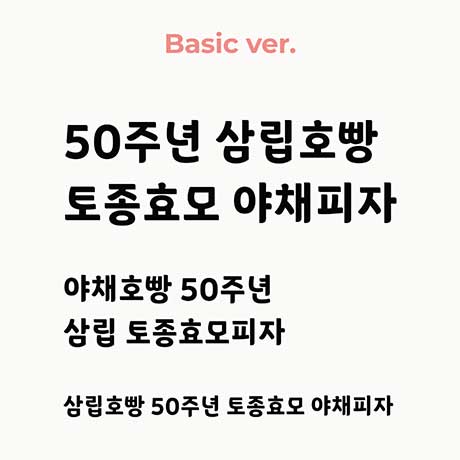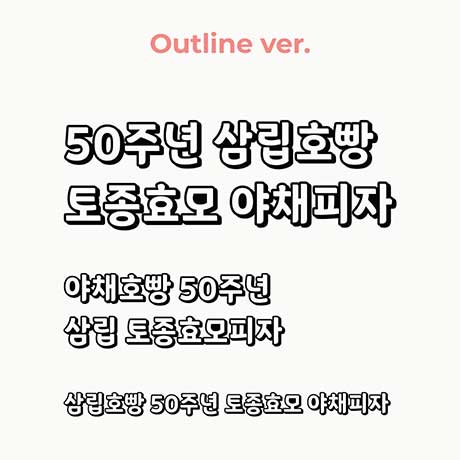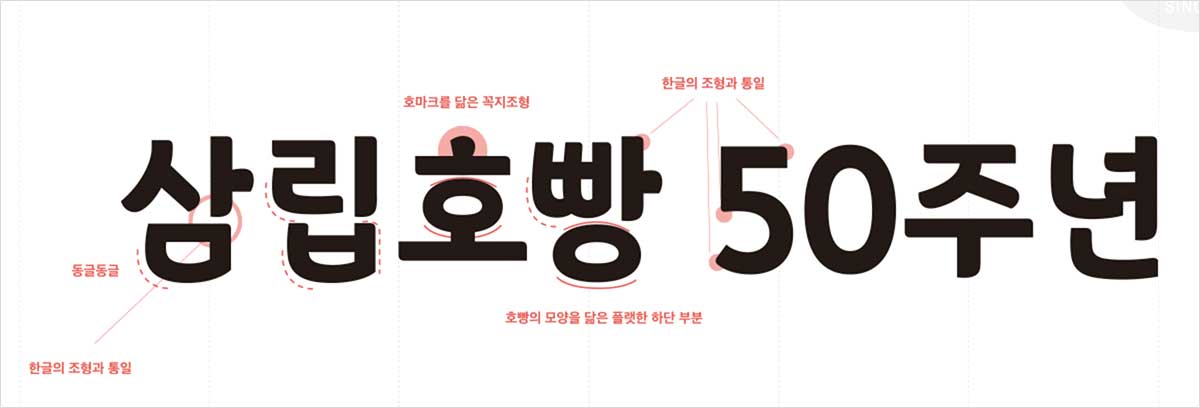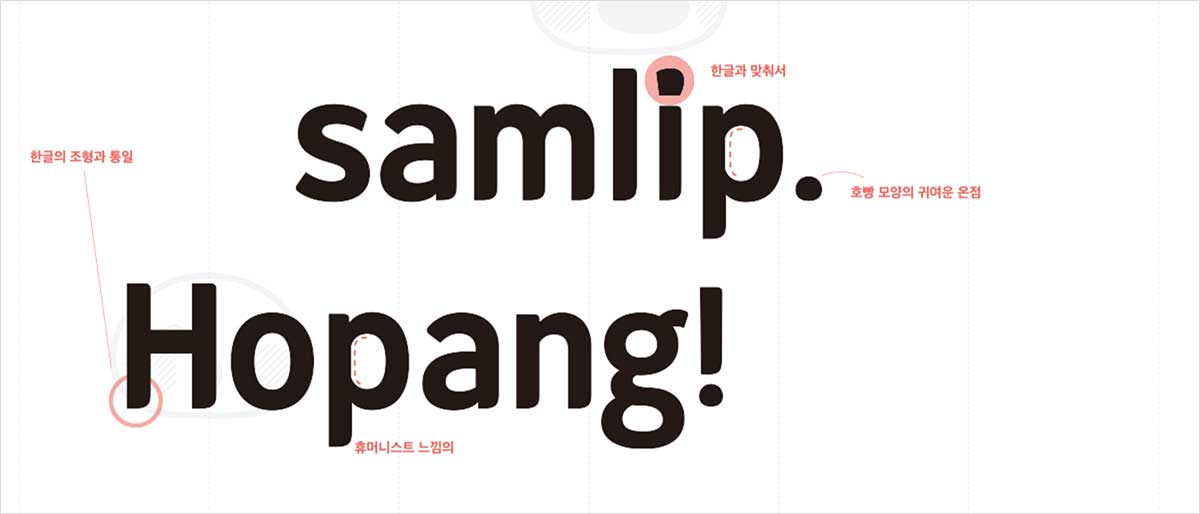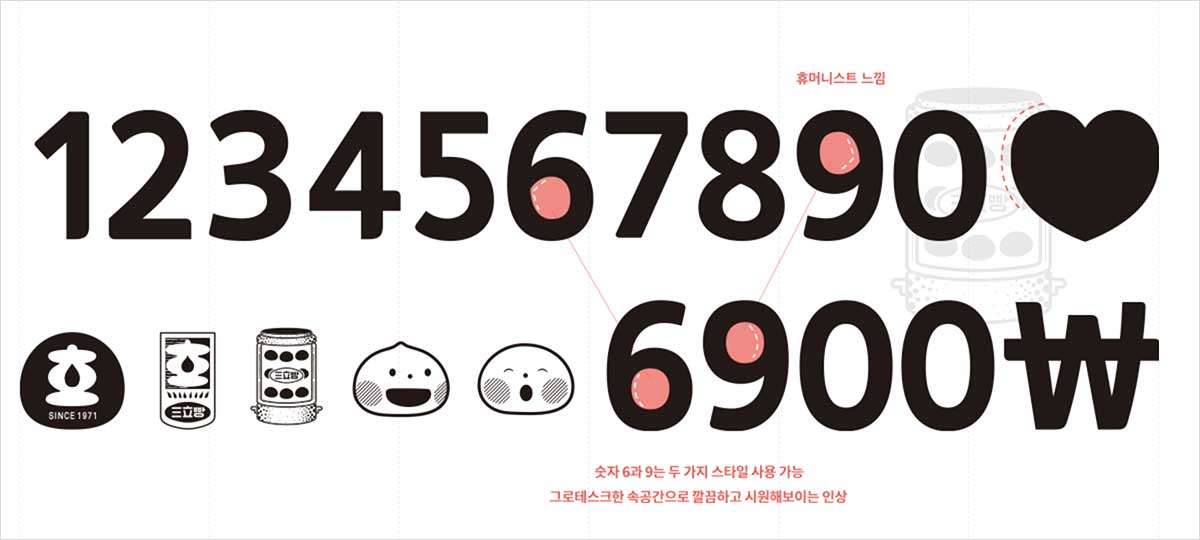
장체 구조의 젊고 캐주얼한 느낌을 가지면서 ‘호호~ 호빵’이 떠오르는 룩의 이 서체는, 삼립호빵의 기존 BI를 기반으로 호빵의 모습이 더 잘 연상되는 동글동글하고 통통한 느낌을 담은 자소 디자인을 추가하여, 삼립호빵 서체만의 개성이 드러나도록 해 주었습니다. 이러한 곡선적 자음들을 직선적 모음들이 잘 잡아주고, 서로 잘 어우러져 캐주얼한 룩을 줍니다.
기본 스타일과 테두리 스타일(Outline)로 제공됩니다.
한글 2,780자
특징❶ 왼쪽 세로획과 오른쪽 획의 비대칭 균형
왼쪽 세로획의 둥근 자소 디자인에 반해 위쪽과 오른쪽의 획은 직선으로 잡혀있는 모습을 특히 ㄴ,ㄷ,ㄹ,ㅁ,ㅂ 자음에서 더 잘 찾을 수 있는데, 이런 특징들이 호빵의 시각적 이미지를 표현해 내면서도 좋은 가독성을 줍니다.
특징❷ 호빵의 모습을 꼭 닮은 ㅇ의 디자인
‘ㅇ’의 위쪽은 살짝 볼록하게, ㅇ의 아래쪽은 상대적으로 플랫 하게 디자인되어 호빵의 귀여운 모습과 유사한 아이덴티티를 보입니다.
특징❸ 호마크를 닮은 ㅎ, ㅊ의 꼭지 조형
라틴 95자
기존의 한글의 획과 맞게 손글씨의 맛을 살린 휴머니스트 스타일의 라틴으로 디자인을 진행하였습니다.
딩벳 14자
호빵을 닮은 온점의 디자인처럼, 서체의 룩에 맞춰 제작된 기본 문장부호와 통화기호, 저작권 마크, 즐겨 쓰는 특수문자 등이 포함되어 있습니다. 딩벳은 총 14가지로 호마크, 호빵, 찜기 등 삼립호빵 하면 생각하는 아이콘들로 구성되어 있습니다.